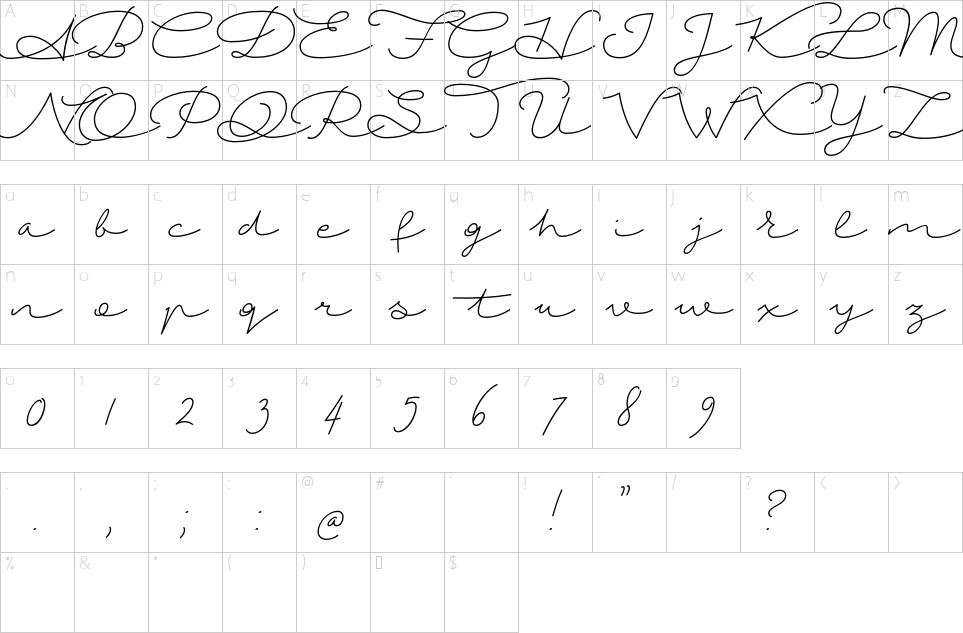
Descubra o encanto da fonte Autumn Chant, uma opção gratuita e cheia de vida que combina perfeitamente com qualquer projeto visual. Desenvolvida por Runes & Fonts, esta fonte vem com uma variedade de tipografias elegantes e sutis, perfeita para textos de página principal ou design gráfico de newsletters. Com seu design minimalista e moderno, a Autumn Chant é ideal para quem procura uma fonte de qualidade sem custos. Esta fonte tem sido baixada mais de 65,281 vezes, evidenciando seu valor e popularidade entre designers e criadores de conteúdo. Seja você um iniciante ou profissional, a Autumn Chant font é uma escolha inteligente para aqueles que buscam estilos únicos sem precisar gastar dinheiro extra. Experimente hoje e deixe sua arte ganhar vida com a elegância e sofisticação desta fonte única.